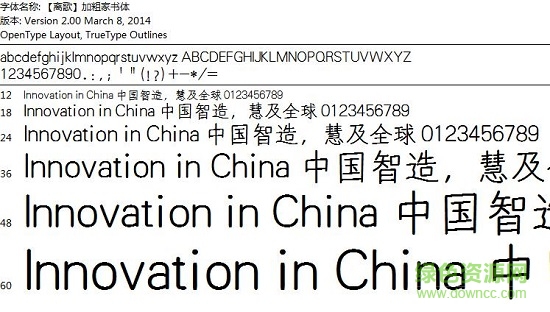
加粗家書體
加粗家書體是一款手寫風(fēng)格的字體,這款字體最大的特點(diǎn)就是非常的整齊,筆畫也很清晰,有需要用到這款字體的朋友,可以來綠色資源網(wǎng)免費(fèi)下載使用!
加粗家書體簡(jiǎn)介
加粗家書體是一款經(jīng)過加粗之后的常用字體,這款字體非常的清秀美觀,看久了也不會(huì)覺得非常的乏,所以適合用來寫家書!